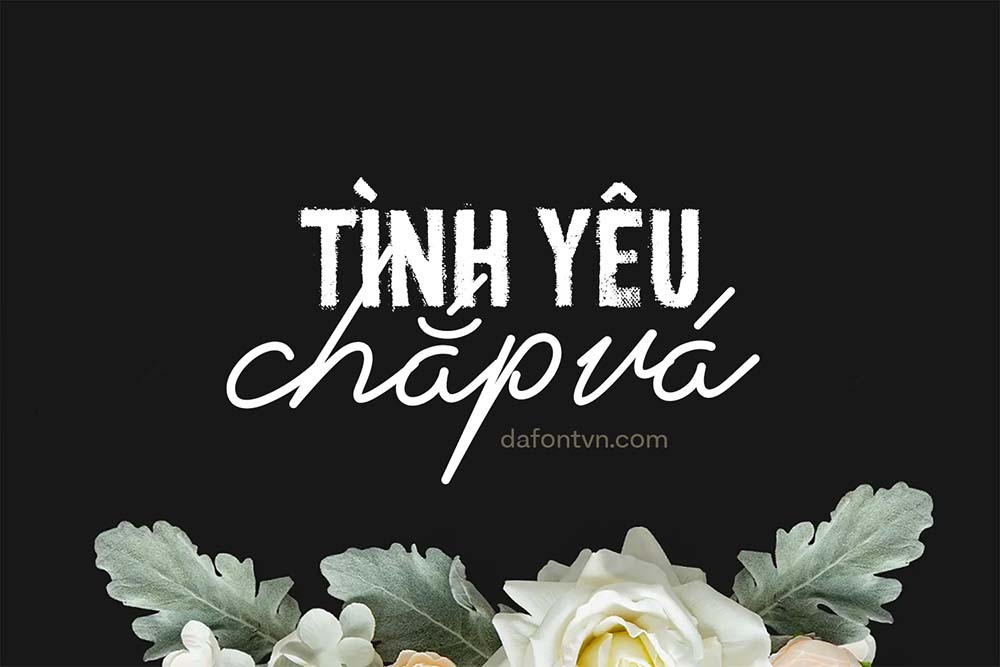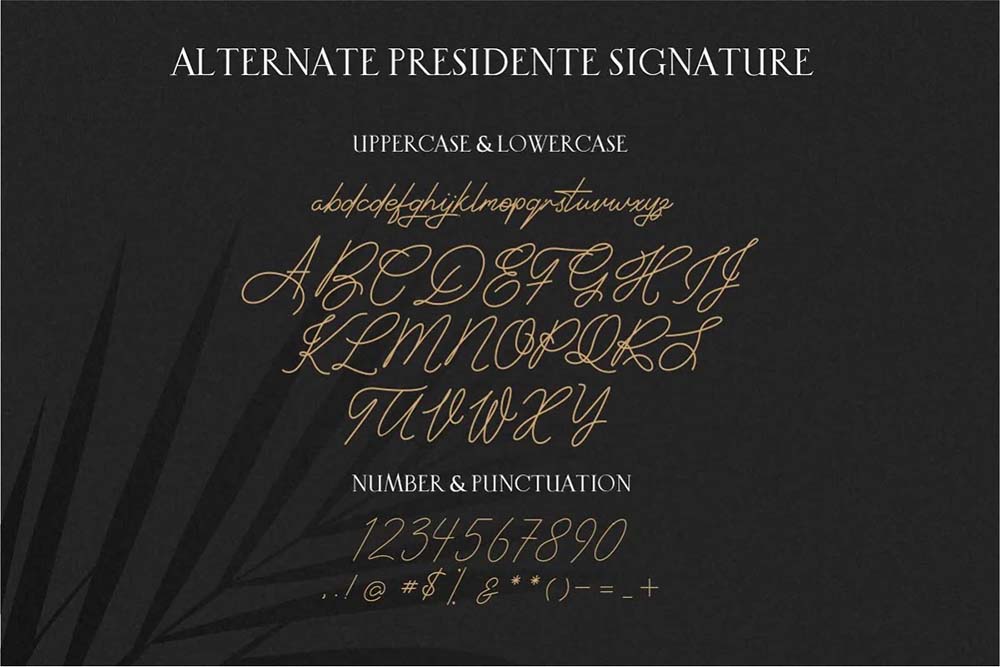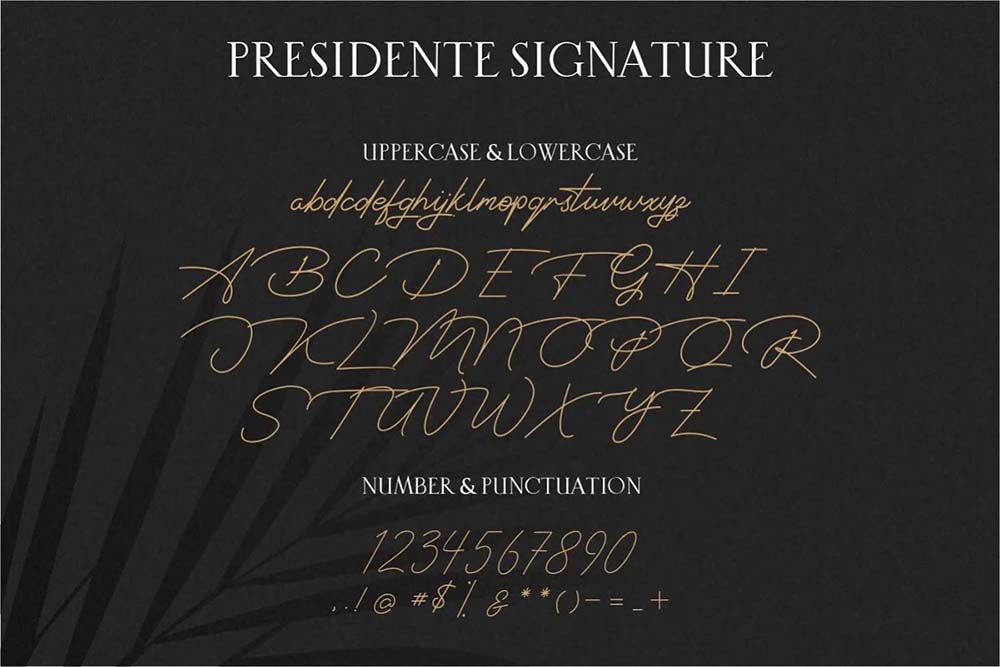
Font Chữ Ký Việt Hóa - Presidente Mang Phong Cách Sang Trọng, Thanh Lịch
Presidente là font script chữ ký thanh lịch rất đẹp, sang trọng, lịch lãm và cao cấp phù hợp cho mọi thiết kế của bạn. Font Presidente Việt Hóa đầy đủ và kerning tiếng Việt hoàn chỉnh, ngoài ra font được tối ưu hóa giúp việc thao tác trên điện thoại nhanh hơn.